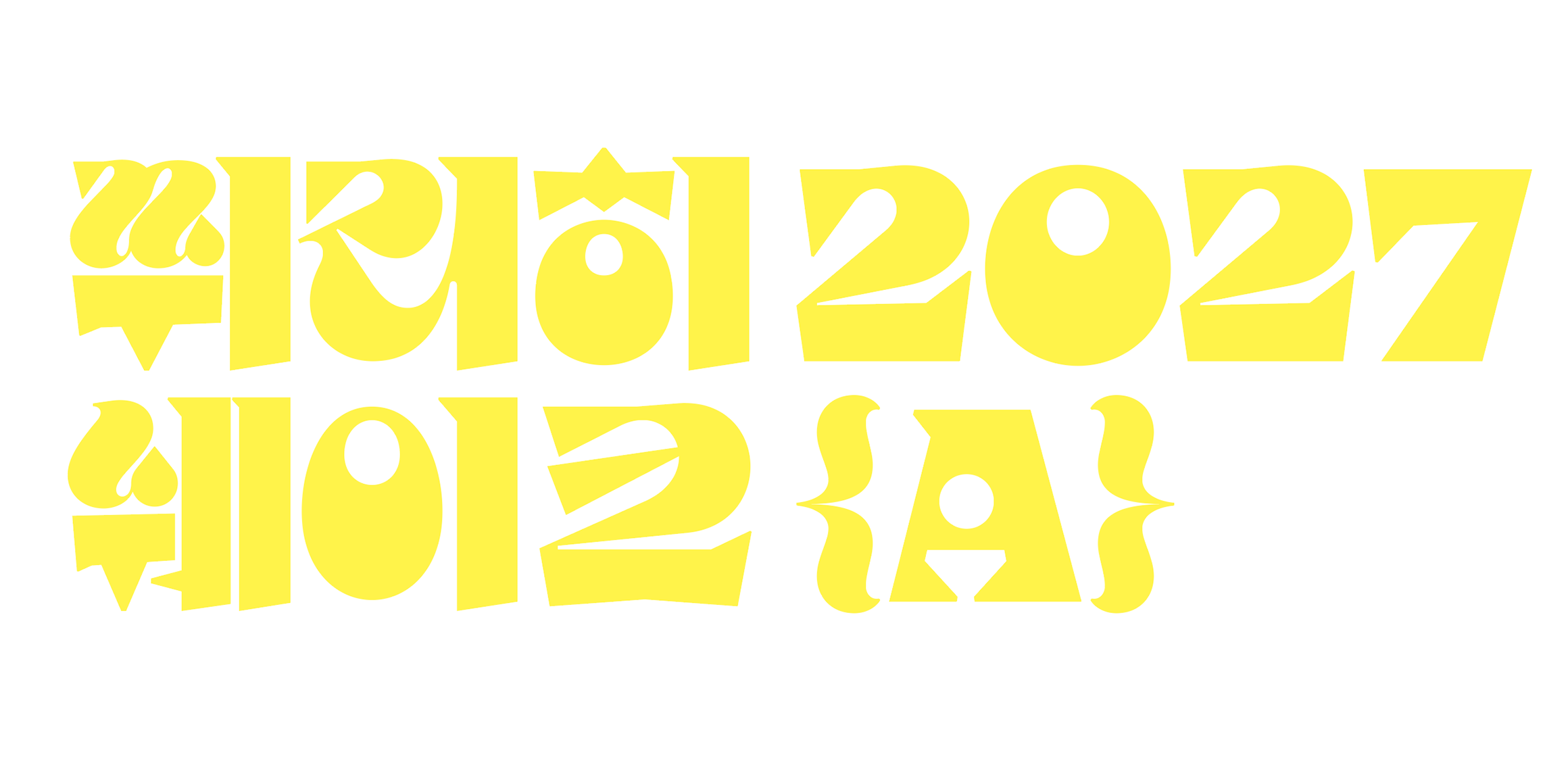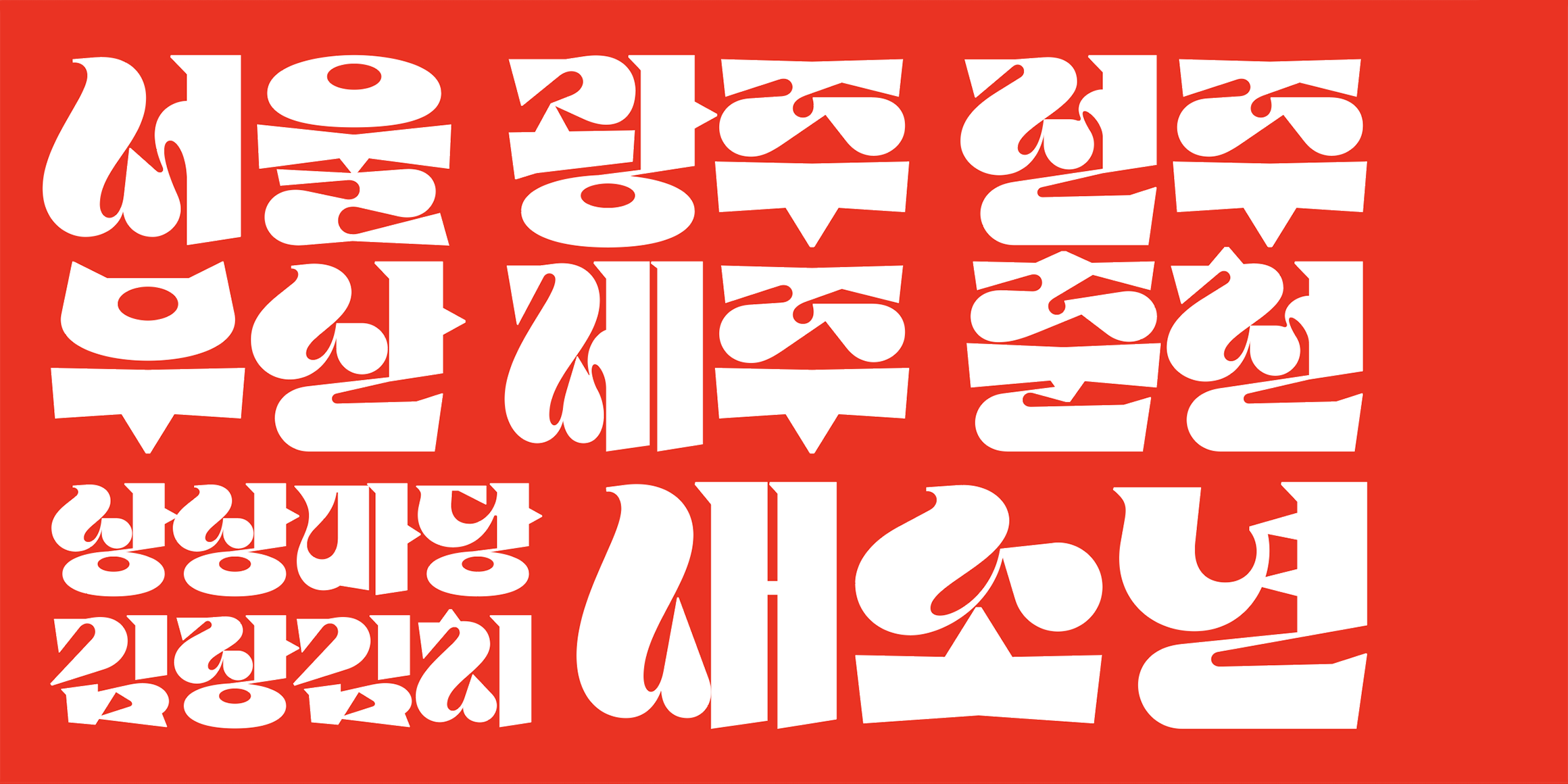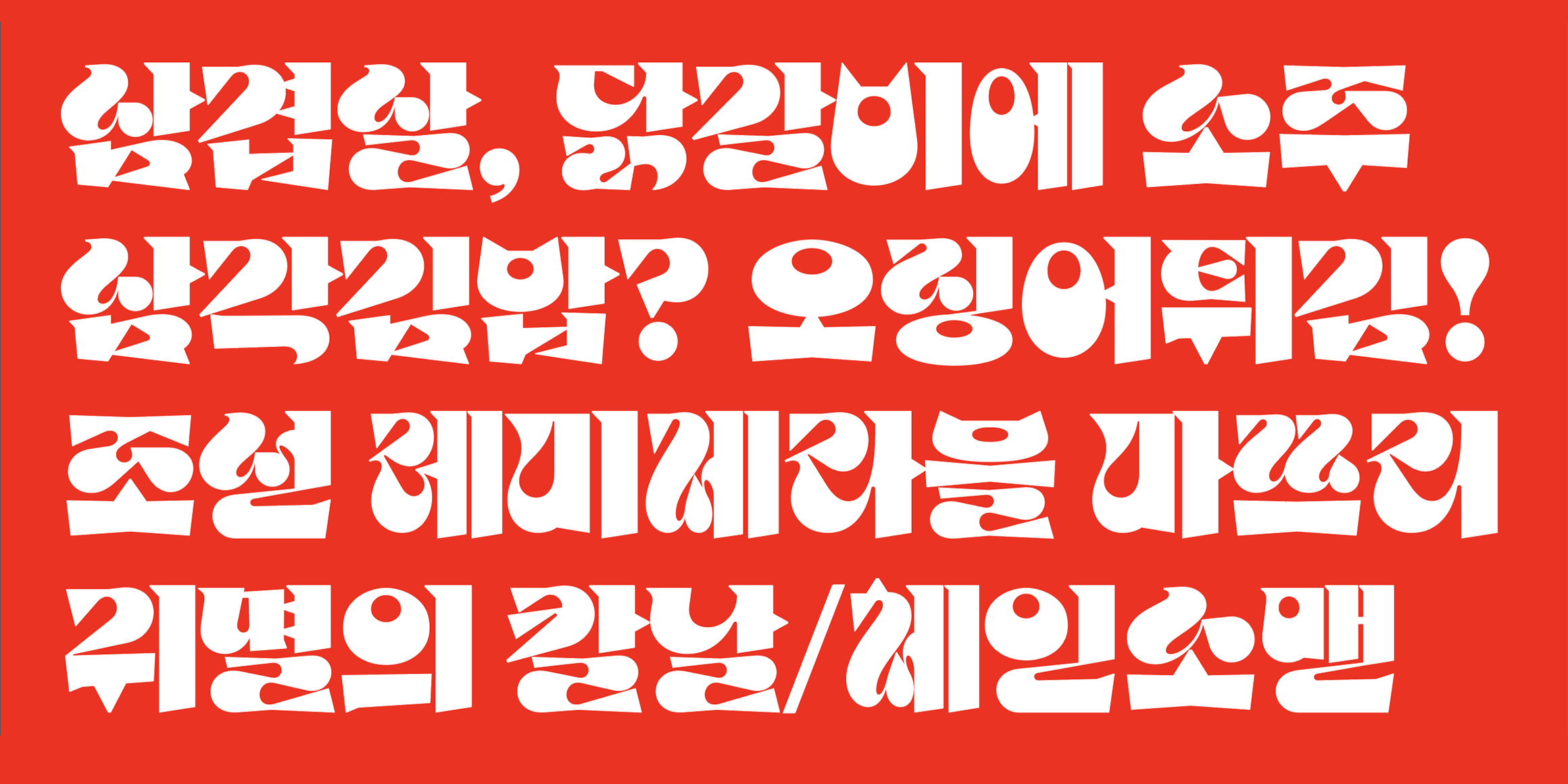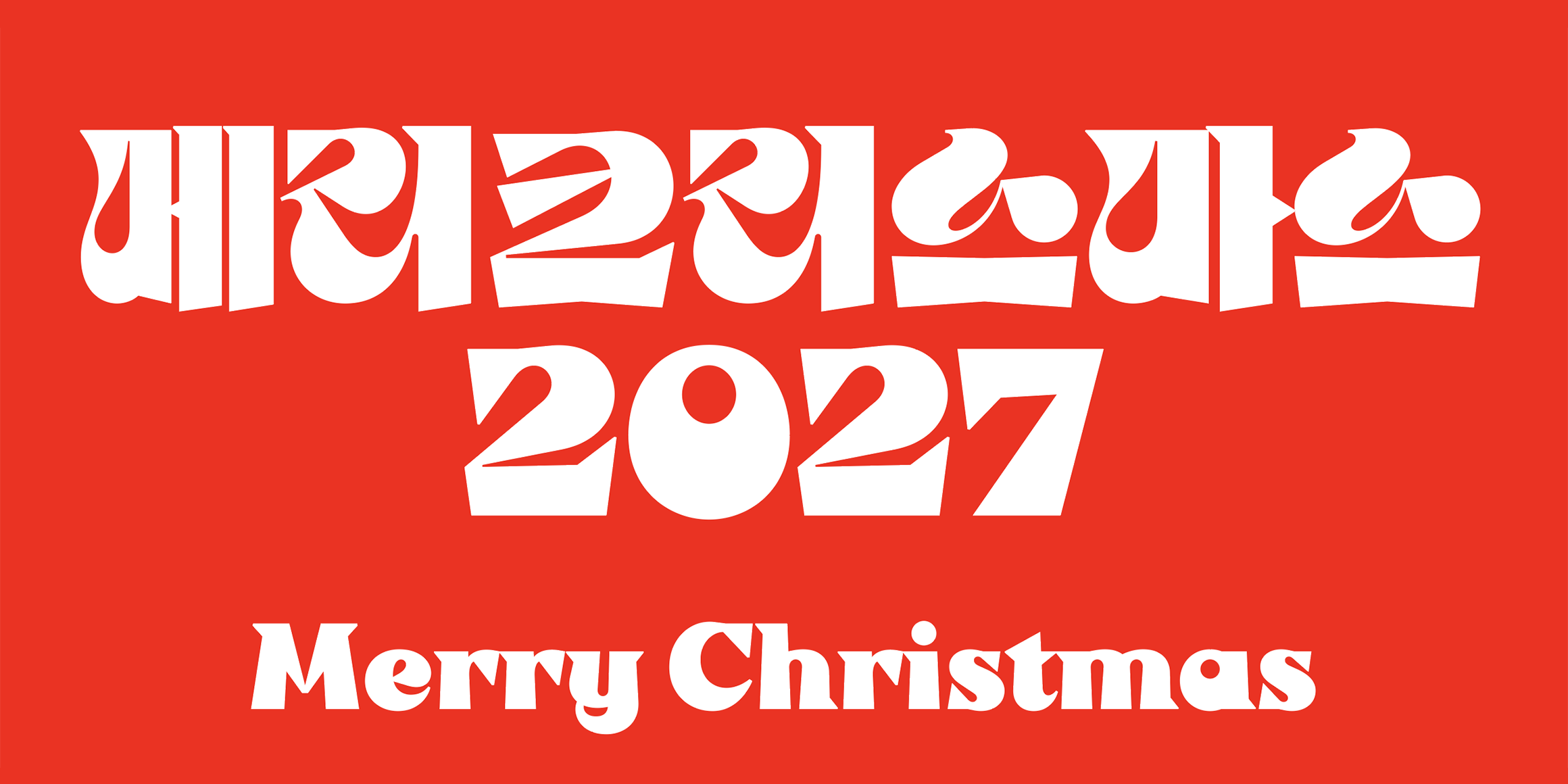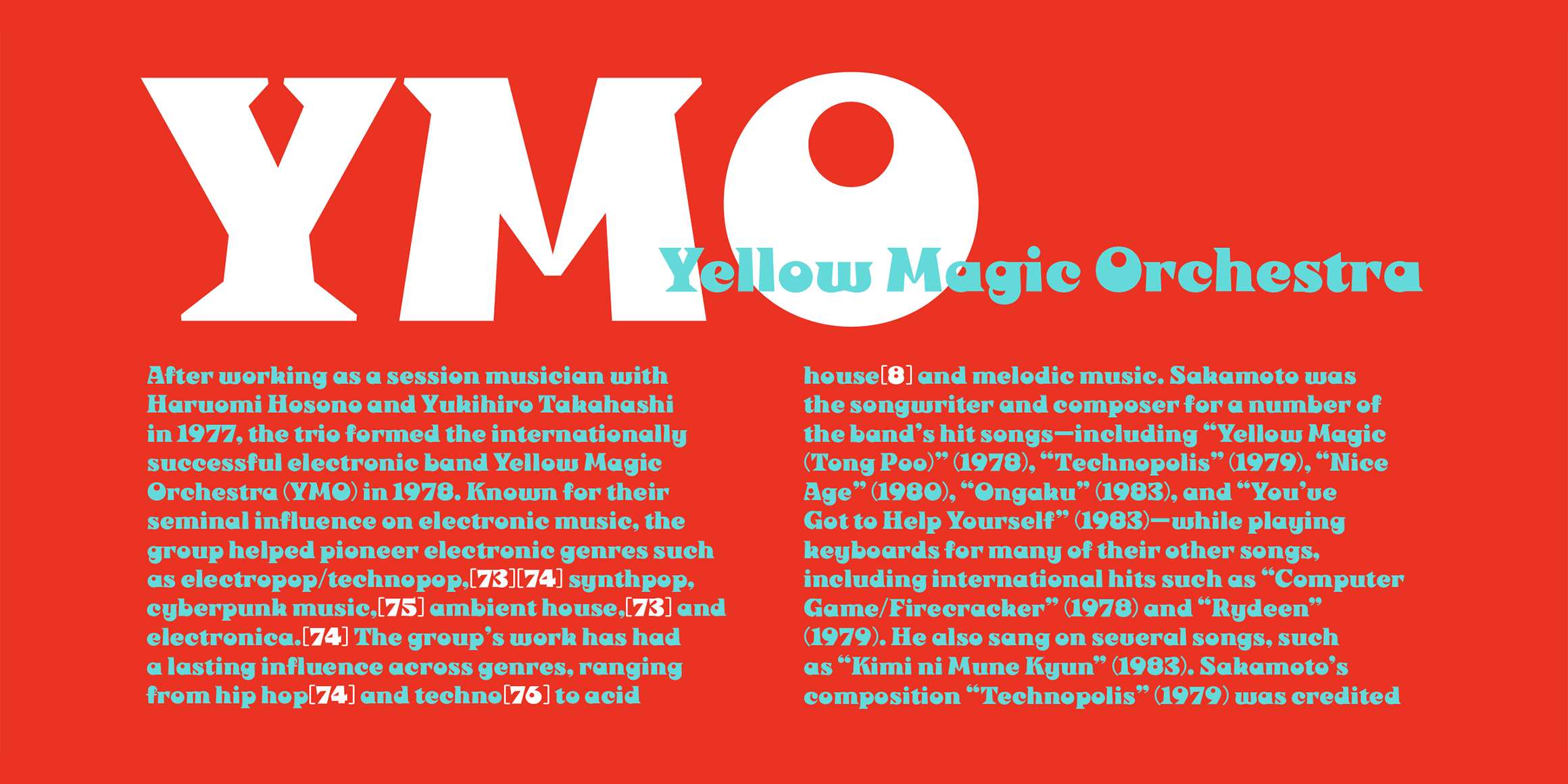
310 팻보이
Ahnsamyeol
분류 Display,디스플레이
제목용현대적개성적
고딕의 단단한 구조에 흘림체의 유려한 리듬을 더하고, 그래피티의 자유분방한 에너지를 담아낸 폰트입니다.
• 안삼열
• Display,디스플레이
• 310 팻보이 / 310 FatBoy
• 제목용,현대적,개성적,귀여운